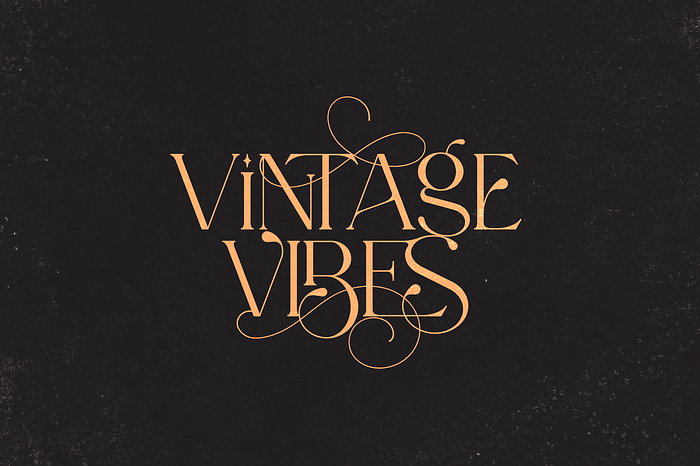
Descubre las Mejores Tipografías Gratuitas para tus diseños
Elegir la tipografía adecuada es muy importante si queremos que el impacto visual de tu proyecto sea el adecuado.
Brenat
Brenat, una moderna y versátil fuente Sans Serif en capas que combina sofisticación con un toque de estilo contemporáneo. Diseñada con precisión y atención al detalle, Brenat está diseñada para elevar tus proyectos creativos a nuevas alturas. Sus líneas limpias, proporciones equilibradas y opciones de capas únicas la convierten en una opción destacada para una amplia gama de aplicaciones.
KRICO
Krico es una fuente con un atractivo estilo de burbujas de ViactionType. Disponible en 6 opciones de estilo, perfecta para diseños con temáticas retro, divertidas y para niños.
Enchanted Tales
Una cautivadora fuente serif que ofrece una mezcla de elegancia clásica y versatilidad moderna, lo que la convierte en una elección ideal para una amplia gama de proyectos creativos. Esta fuente cuenta con un impresionante soporte para 87 idiomas, asegurando accesibilidad global e inclusividad en tus diseños. Una de las características más destacadas de Enchanted Tales es su extensa colección de más de 150 glifos de ligadura, cada uno meticulosamente elaborado para agregar un toque único de sofisticación y estilo a tu texto.
Quakers Retro Bold Script
Es la evolución de la fuente ‘Cuanky’, en su versión itálica, transformada en una cautivadora fuente de script. Abrazando la esencia del diseño retro, Quakers irradia un aura de elegancia vintage combinada con audacia y elegancia modernas.
Anti Design Endeavour
El equilibrio se puede lograr a través del contraste, el color o cualquier otra cosa, y también puede ser asimétrico. Al combinar varios tipos de fuentes, como cursiva, serif, script y vintage, consiguen establecer un equilibrio asimétrico manteniendo la armonía.
Lokanova
Es una tipografía sans serif diseñada en un estilo moderno y único para dar la impresión de un diseño firme. Lokanova está disponible con mayúsculas, minúsculas, números, símbolos y multilingüe.
Keyute
Una fuente de Dryy.type que encarna todo el encanto lúdico y caprichoso de la actual tendencia K-POP. Creada con versatilidad en mente, esta fuente es la elección perfecta para elevar tus diseños al siguiente nivel.
Angel Club Font
Tipografía serif retro, con cuatro tipos de fuentes en este paquete, versión Regular, inclinada y sombreada. ¡Usa esta fuente de exhibición para añadir ese toque retro especial a cualquier idea de diseño que se te ocurra!
Super Vibes Font
Tipografía con estilo retro y dinámico, perfecta para resaltar tus proyectos de diseño con un aire nostálgico. Esta excepcional fuente de presentación ha sido cuidadosamente elaborada para ser un verdadero tesoro en tu colección, con el poder de elevar cada una de tus ideas creativas a nuevas alturas. ¡Inclúyela en tu próxima creación y observa cómo aporta un encanto especial del pasado!
Katherine Thompson
Esta tipografía, perfecta para añadir un toque de sofisticación despreocupada. Con su fácil legibilidad, esta fuente es sumamente versátil y se adapta con estilo a diversos usos: desde branding y logotipos hasta encabezados en blogs, decoración de fotografías y elaboración de marcas de agua. Es ideal para publicaciones en redes sociales, anuncios publicitarios, diseño de productos, etiquetas, papelería, invitaciones de boda, empaques y eventos especiales. Incorpora esta fuente con facilidad a tus proyectos para conferirles una sensación de elegancia casual.
Tropi Land Font
Tipografía sans serif escrita a mano, ondulada, juguetona y natural. Encontrarás muchas ligaduras y caracteres alternativos en ella. Esta fuente es perfecta para crear logotipos, marcas de agua, branding, invitaciones de boda, citas, líneas de etiquetas o cualquier otra cosa. Hagamos algo hermoso con este proyecto.